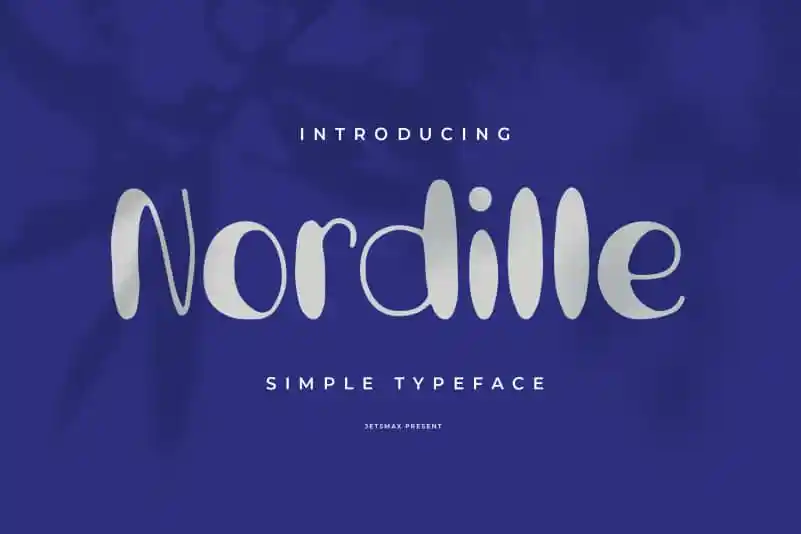
Nordille Display Font – Download Grátis
A Nordille Display Font é uma tipografia de exibição criativa e única, que combina dois estilos distintos: Regular e Outline. Ela oferece um toque autêntico ao seu design, com linhas delicadas e formas dinâmicas trazidas diretamente da mão do artesão. Esta fonte manuscrita é perfeita para quem busca dar destaque a seus projetos de design, criando um impacto visual imediato que se destaca em qualquer layout ou projeto gráfico. Com seu estilo enérgico e seu aspecto elegante, a Nordille Display Font torna-se uma escolha ideal tanto para elementos de título quanto para textos de corpo em designs de alta qualidade. O designer jetsmax capturou a essência desta fonte manuscrita em todas as suas linhas e formas, resultando em um produto único que traz vida e personalidade ao seu trabalho. É uma excelente escolha para quem deseja dar destaque aos seus projetos com uma tipografia distintiva e arrojada, sem se render à facilidade de usar fontes mais convencionais. O resultado é um design atraente e diferenciado que vai chamá-los para o seu trabalho.